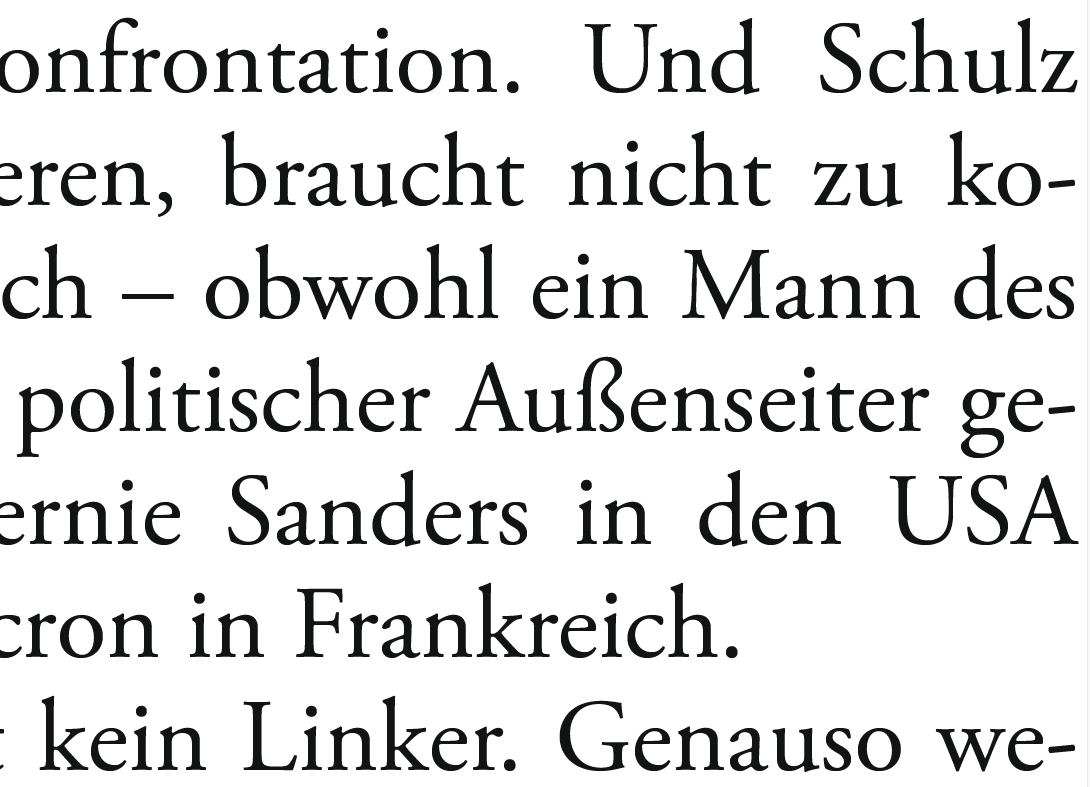
Schrift-Kombi für Projektarbeit im Bereich der Geschichtswissenschaften
Nein nein nein! Nicht extrahieren, sondern identifizieren.
Ich wollte nur wissen welche Fonts Die Zeit in ihren PDF Ausgaben für was benutzt.
Gibt es da ein Tool? (ich probiere es mal mit FontForge)
Leider sind sehr viele Schriften im PDF eingebettet...
Die meisten PDF-Viewer haben im Menu Datei -> Eigenschaften -> Schriften ... Damit wird einem mit etwas Glück die Schrift im Klartext angezeigt. Falls es da aber einen kryptischen Namen gibt ... dann wird es aufwändiger ...
Das Problem ist, dass in dem PDF etwa 200 Schriften verwendet worden sind... man kann nicht sehen, welche genau für was benutzt wurde.
Dann macht es Arnos Extrahiermethode mit Fontforge
Uwes. In den höchst seltenen Fällen, in denen ich Fonts (bzw. die kläglichen im PDF enthaltenen Reste ) extrahiert habe, habe ich mich anderer Tools bedient.
Die 200 in dem PDF enthaltenen Fonts zu extrahieren, ist eine super Methode, um zu prokrastinieren. Das wird dich mehr Zeit kosten, als dir die Grundlagen von LaTex beizubringen.
Wozu braucht die Zeit überhaupt 200 Schriften in einem PDF?
Das habe ich mich auch gefragt, schaut aus, alsob die da generell die komplette Schriftensammlung rein hauen - wohlmöglich sogae nur Leerzeichen, die von irgendwas übrig geblieben sind. Da sollte wohl mal jemand aufräumen?
Aber kann man sich wirklich nicht den Namen einer bestimmten Schrift anzeigen lassen? Das gibt's doch schon für Websiten als Chrome Plug-In.
Wenn es dir nur um eine Schrift geht, dann mach doch einen Screenshot und bitte um Identifizierung. Die Liste mit den 200 Namen kannst du ja deinem Beitrag anhängen (als Text-Datei).
Bei xpdf gibt es da z.B. das Kommandozeilentool pdffonts. Hier mal eine Beispielausgabe:
Beeindruckende Entscheidungsfreude. Warum paßt sie so wirklich gut zum Thema? Und zur Baskerville?
Das Thema bekommt durch die Cinzel gleich etwas Leichtes, Spielerisches, Unverfängliches …
Ich meinte für die Kapitelüberschriften:roll:
Das ist eine klassische Schrift... klar ist sie ein wenig dekorativ, aber doch nicht spielerisch!?
Ich sehe allerdings gerade dass sie für den Bildschirm konzipiert wurde, ist das problematisch?